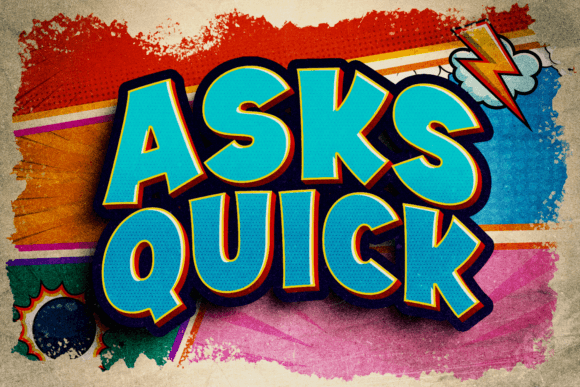
Solicita fuentes rápidas para titulares, carteles y proyectos de marca
Asks Quick es una fuente dinámica de superhéroes para cómics que captura la esencia de la estética clásica del cómic con su diseño audaz, enérgico y divertido. Con sus trazos gruesos y robustos y sus formas vibrantes, Asks Quick irradia energía y movimiento, captando la atención al instante.
- Diseño atrevido y enérgico
- Trazos gruesos y robustos
- Formas de personajes vivaces
- Perfecto para la estética del cómic.
Adecuado para libros infantiles, juegos y materiales educativos que buscan atraer y entretener con un estilo lúdico y aventurero.